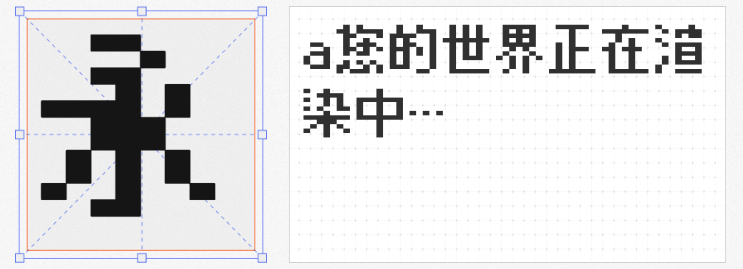
在设计领域,标题字体是吸引观众注意力的关键元素。无论是海报、广告还是品牌标识,一款风格独特的标题字体都能瞬间提升整体设计的质感。今天,我们精选了四款免费商用、适用于标题设计的字体,它们各具特色,能够满足不同场景的需求。
1. 仓耳非白 W05
仓耳非白 W05以强烈的粗细对比和简洁的几何结构脱颖而出。其笔形利落,转折处均为直角,撇捺以直线表现,形成鲜明的视觉张力;而圆形的点元素与方正结构结合,又为整体增添了一丝柔和感。这款字体适合科技、时尚或现代感强的设计主题,能够快速抓住观众眼球。
2. 仓耳与墨 W04
仓耳与墨 W04以篆刻的“刀意”为灵感,笔形模拟刀刻痕迹,呈现出厚重、前卫的视觉效果。为中和尖锐感,字体在转折和“口”字结构上采用圆转角设计,形成“内方外圆”的独特风格。配套的英文和标点符号延续了中文的设计语言,混排时和谐统一,非常适合品牌主视觉或文化类海报。
3. 目哉像素体 Flat
基于8x12点阵的目哉像素体 Flat,以清晰的像素颗粒感还原了经典游戏与数字时代的复古美学。这款字体适用于电子、游戏或科技主题的设计,既能传递怀旧情怀,又能通过简洁的像素风格展现现代感,尤其适合作为标题或标语使用。
4. Aa厚底黑
Aa厚底黑通过窄长字形与大弧度曲线的设计,打破了传统黑体的沉闷感。加厚的底部笔画为字体注入活泼气质,适合年轻化、潮流向的设计场景,如运动品牌、音乐节海报或社交媒体内容标题,能够轻松营造轻松有趣的氛围。